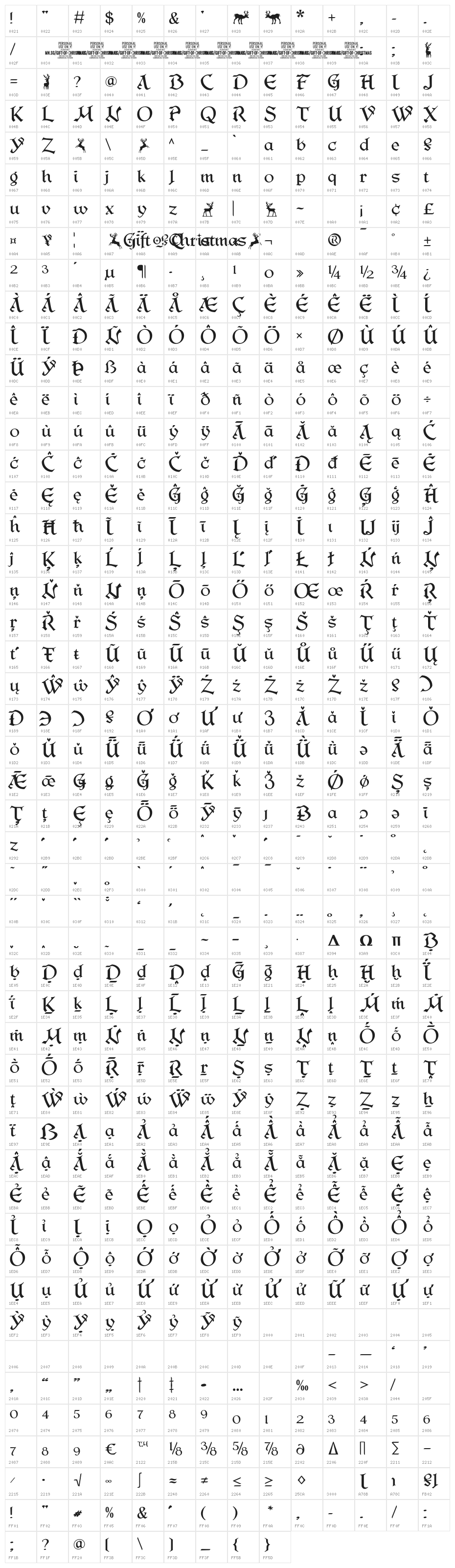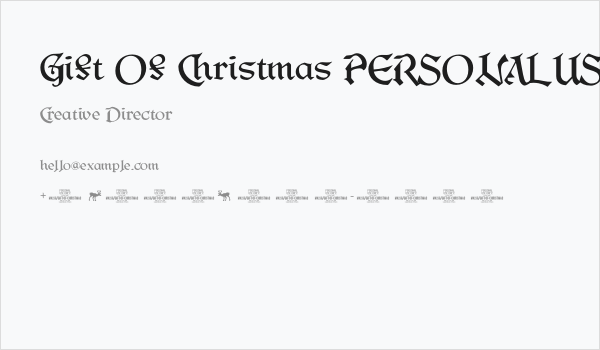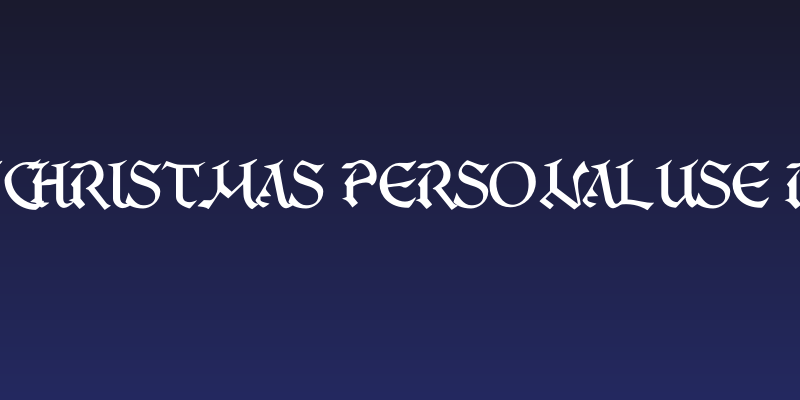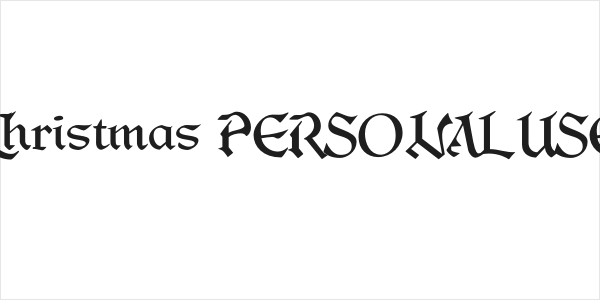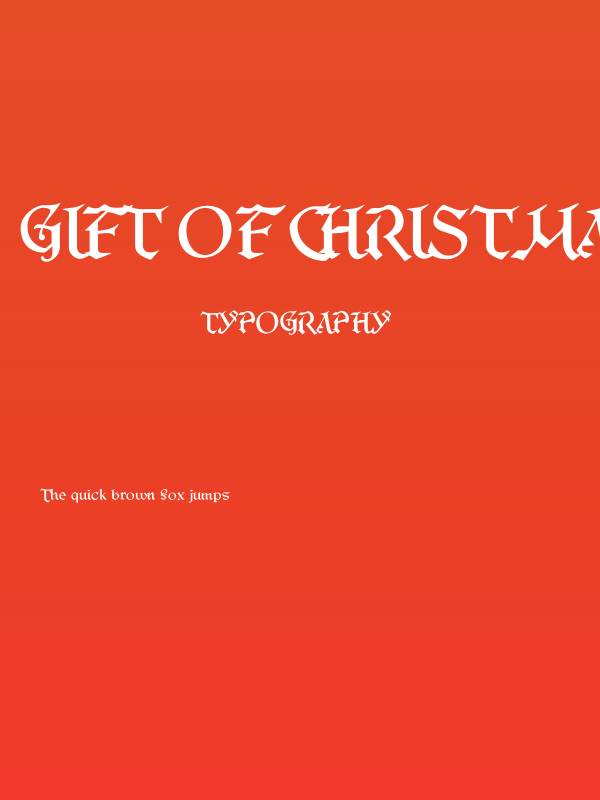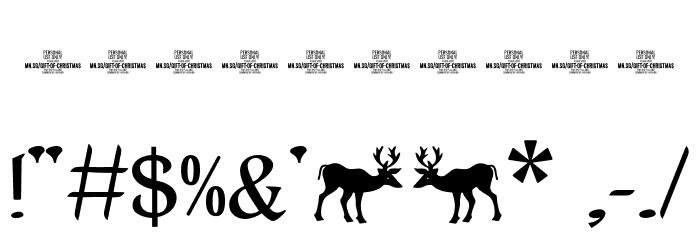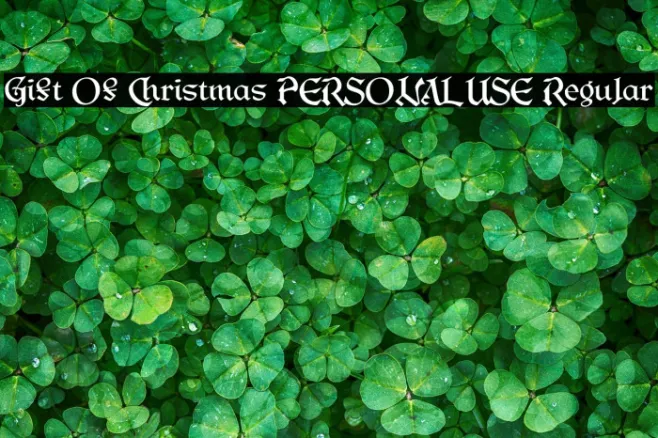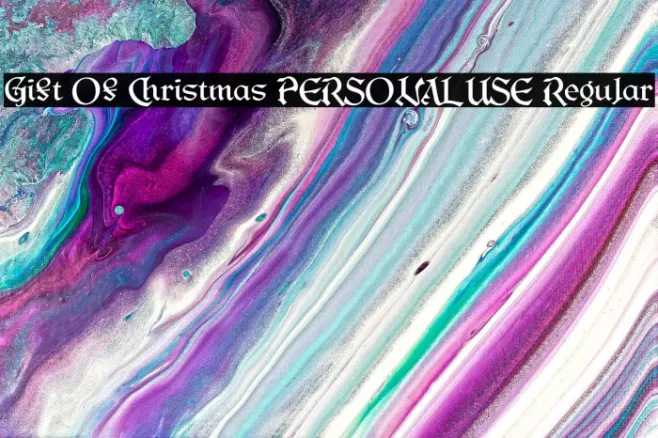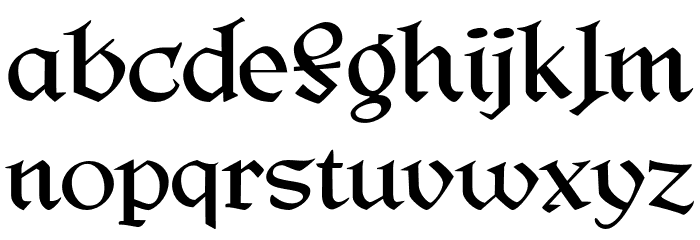
Gift Of Christmas PERSONAL USE Regular Font
✎ Gothic
| Kategorien | Gothic |
| Gesamtstil | Vintage |
| Anwendungsfall | Logos, Headlines, Decorative text |
| Vorgeschlagene Projekte | Ideal for holiday cards, invitations, historical documents, or any project needing a traditional, medieval touch. |